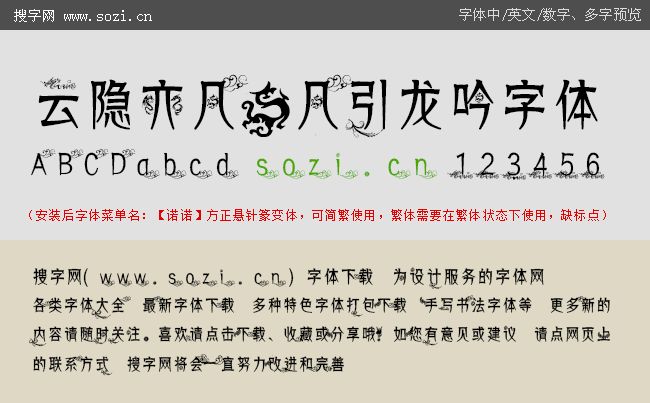
云隱亦凡@凡引龍吟字體
搜字網(wǎng)給大家提供一款云隱亦凡@凡引龍吟字體手機中文字體下載。這款手機字體是在方正懸針篆變簡體筆畫間插入了龍紋與云紋圖案裝飾。方正懸針篆變字體意在保留篆書韻味,同時將隸書與楷書筆畫特征熔于一爐,端莊秀美、開張疏朗,雍容大氣、復古卻易讀。加入了圖案后又增添了趣味性,特別適合喜歡手機字體個性一些的朋友在手機上安裝使用。